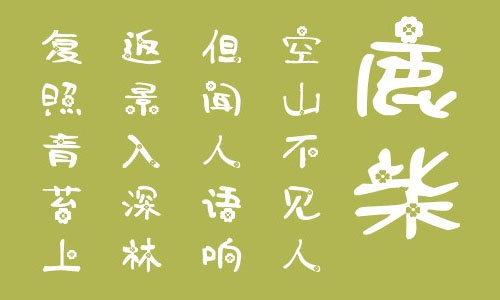
南構(gòu)花韻字體是一款字形中帶有各種花圖案的中文藝術(shù)字體,該字體古香古色,剛毅而又嚴(yán)謹(jǐn),整體效果非常的出色,可以廣泛應(yīng)用于廣告設(shè)計(jì)、宣傳海報(bào)、ppt、影視制作以及任何使用文字的領(lǐng)域,歡迎有需要的朋友前來(lái)下載使用。